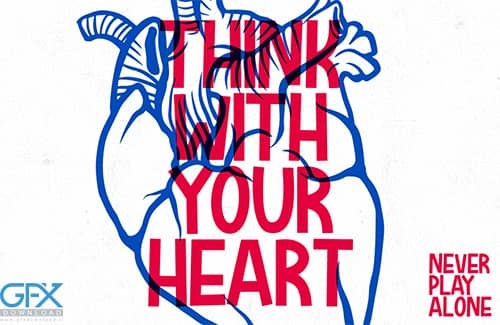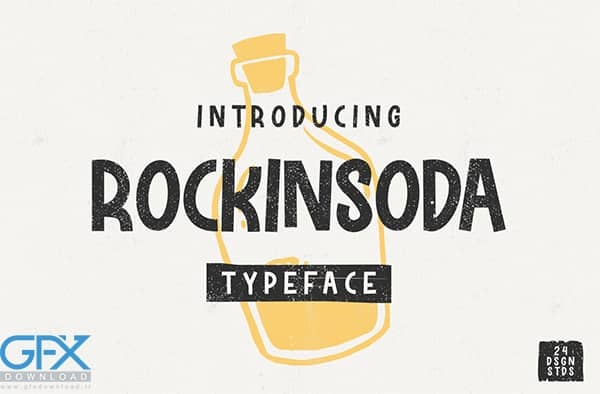
دانلود فونت کودکانه Rockinsoda
فونت فانتزی کودکانه Rockinsoda
دانلود رایگان فونت انگلیسی کودکانه Rockinsoda
یک فونت نمایشی و زیبا با استایل دست خط کودک است ، اگرچه در پیش نمایش این فونت ها همه حروف های بزرگ هستند ولی دارای حروف کوچک نیز است. این فونت برای هر چیزی که مربوط به غذا ، بچه ها ، آثار هنری بچه ها ، عناوین کتاب ، عنوان وب سایت ، نوشتن ویدیو یا هر چیز دیگری است که می توانید از آنجا بدست آورید مناسب است. .اگر به دنبال فونت مناسب برای استفاده در اهداف ویژه مناسبت های مربوط به کودکان هستید با دانلود فونت کودکانه Rockinsoda این فرصت را از دست ندهید.